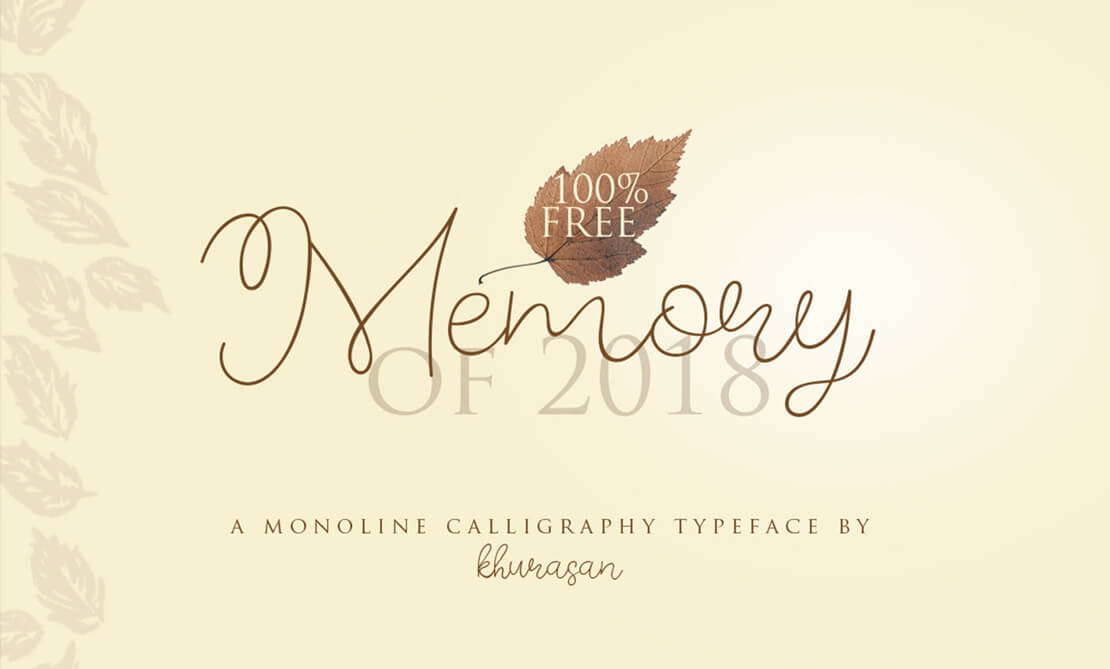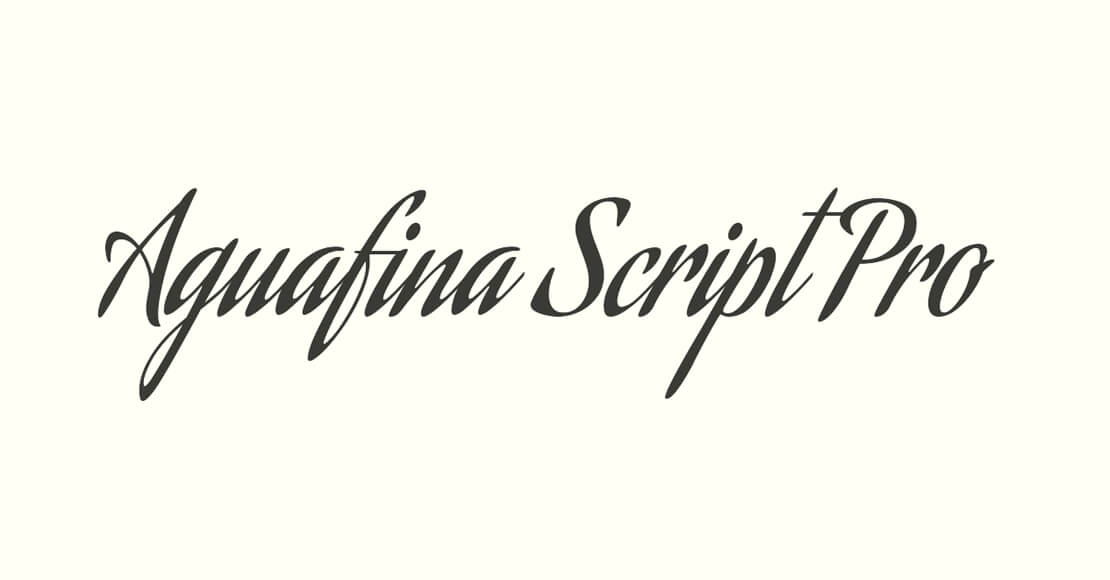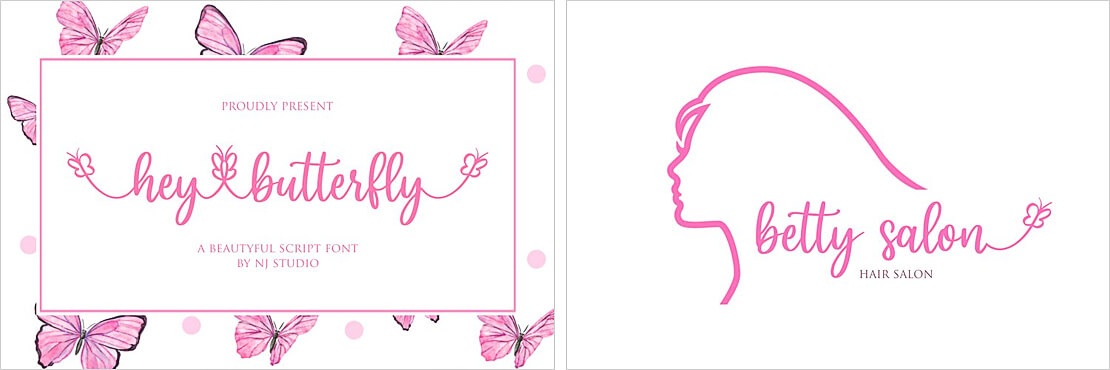
Kalligraphie-Schrift: Kostenlose Fonts zum Downloaden
Kalligraphie-Schrift ist beliebt. Moderne Fonts verwenden OpenType-Features, um die „Kunst des schönen Schreibens“ möglichst natürlich bzw. realistisch wirken zu lassen. Hier kommen ausgesuchte und zudem kostenlose Kalligraphie-Schriften.
Traditionelle und moderne Kalligraphie
Bei der Kalligraphie geht es im Grunde genommen um das schöne (kunstvolle) Schreiben. Die traditionelle Technik folgt dabei bestimmten Regeln. Diese geben beispielsweise vor, auf welche Weise Buchstaben zu formen oder auszurichten sind. Die entsprechende Ästhetik wird zumeist durch ein hohes Maß an Perfektion erreicht.In der modernen Kalligraphie hingegen spielen die klassischen Vorgaben eine eher untergeordnete Rolle. Vielmehr ist Individualität gefragt. Da darf es dann auch mal wilder zugehen. Die Persönlichkeit bzw. das Transportieren von Gefühlen, Emotionen etc. steht im Vordergrund. Somit eignen sich moderne kalligraphische Schriftarten beispielsweise auch fürs Branding von Marken, zur Verwendung in Kalendern, in persönlichen Instagram-Stories und mehr.
Alternative Zeichen, Ligaturen etc. bei Kalligraphie-Schriftarten
Moderne Kalligraphie-Schriftarten setzen verstärkt auf OpenType-Features, um eine möglichst natürlich wirkende Schriftart zu erzielen, die wie von Hand mit der Feder geschrieben aussieht.
Durch die Schrift-Technologie können verschiedene Varianten von Buchstaben in einem Font gespeichert und bei Bedarf abgerufen werden. Auch mehrere Kombinationen von Buchstaben bzw. Ligaturen sind dementsprechend möglich (beispielsweise „fl“, „st“, „ll“ etc.). Häufig findet man bei Kalligraphie-Schriftarten auch opulente Anfangsbuchstaben oder schmückende Elemente wie Striche oder weitere Ziersymbole, die ebenfalls in den Fonts fest integriert sind.
Kostenlose Kalligraphie-Schrift zum Downloaden
Endestry Kalligraphie-Schrift
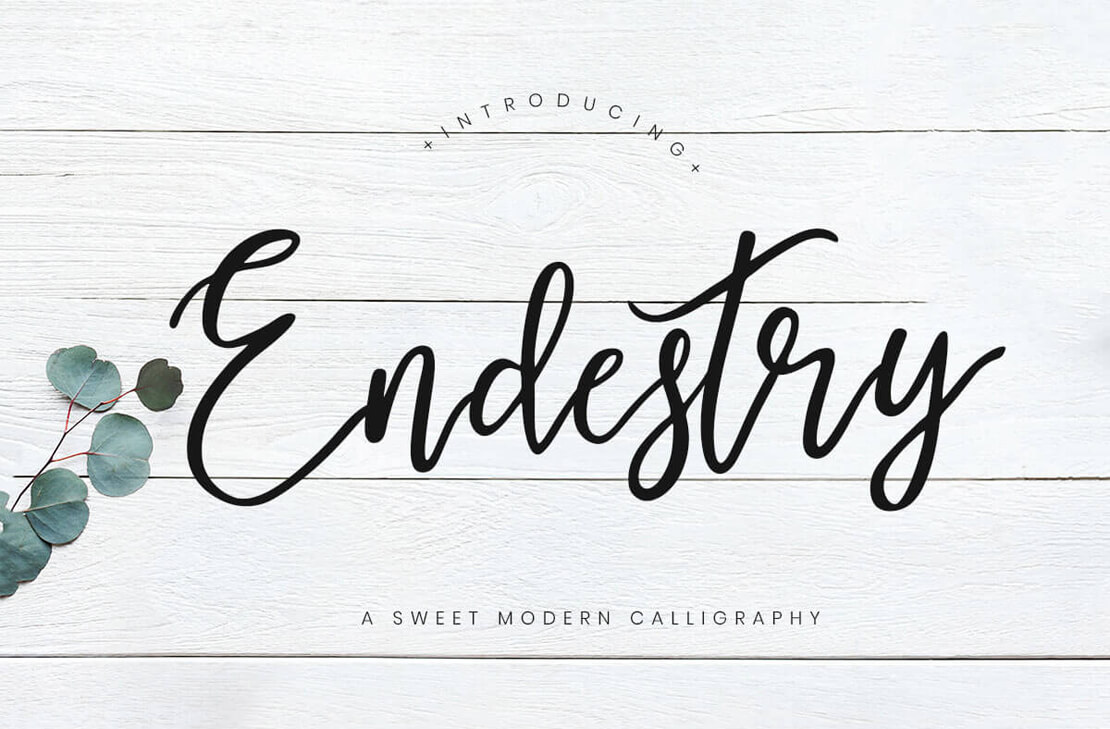
Endestry ist ein moderne Kalligraphie-Schriftart aus der Feder von Creatype Studio. Die geschmeidige Schrift sorgt zudem für eine persönliche Note und lässt sich für unterschiedliche Design-Projekte verwenden. Gemäß den Angaben auf der Website ist die Nutzung für private und kommerzielle Projekte kostenlos.
Kallem
Diese kostenlose Kalligraphie-Schriftart wurde von Khaiuns gestaltet. Der Font enthält neben Groß- und Kleinbuchstaben außerdem Symbole, Ligaturen und weitere Zeichen. Zudem werden mehrere Sprachen unterstützt. Die sogenannte „Free Version“ darf für private und kommerzielle Projekte verwendet werden. Außerdem gibt es noch eine erweiterte Version der Schrift, die noch mehr Zeichen enthält.
Basyirah Script: Kalligraphie-Schriftart
Ein Font mit ansprechender Handkalligraphie. „Basyirah Script“ lässt sich vielfältig verwenden – beispielsweise für Hochzeitseinladungen, Etiketten, Poster, Zitate, Beschilderungen und mehr. Der Download wird unter der sogenannten „Premium License“ angeboten. Dementsprechend lässt sich dieser Kalligraphie-Font für kommerzielle und private Zwecke gleichermaßen verwenden.
Rachella Script Font
„Rachella Script“ stammt Ian Mikraz Studios Sammlung von kostenlosen Kalligraphie-Schriftarten. Der Font enthält 270 Glyphen und 87 alternative Zeichen. Enthalten sind außerdem stylistische Alternativen, Ligaturen und mehr. Außerdem werden OpenType-Funktionen unterstützt. Den Free Font kann man übrigens direkt von der Website des Type-Designers herunterladen.
Mr De Haviland aus der Charles Bluemlein Script Collection
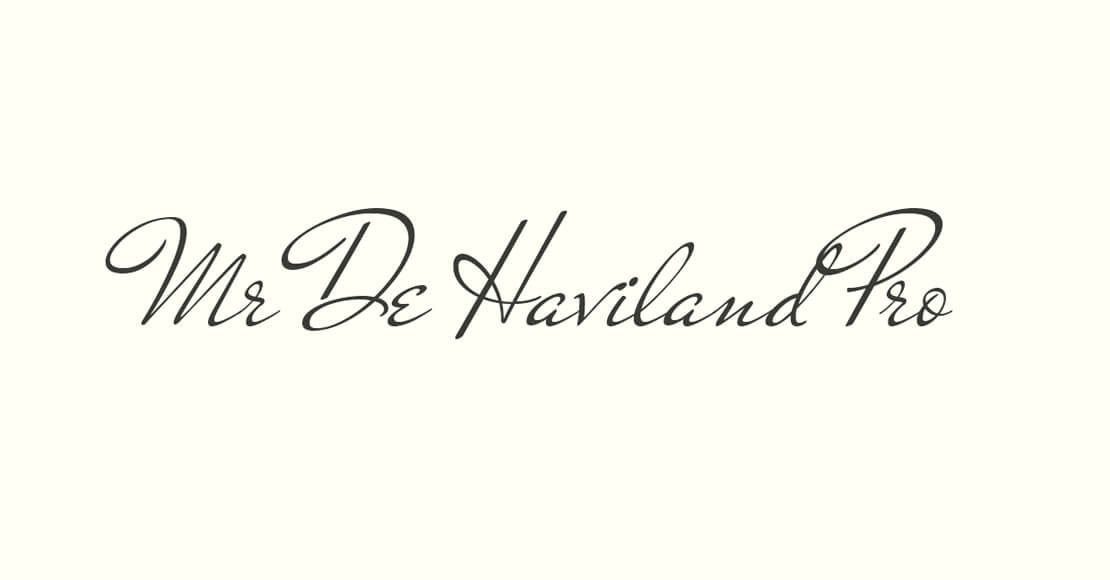
Die „Charles Bluemlein Script Collection“ ist eine Hommage an die Handschrift-Schriftarten und Kalligraphie-Fonts der frühen 1930er Jahre. Sudtipos digitalisierte sorgfältig die New Yorker Sammlung und präsentiert mit „Mr De Haviland“ eine ausdrucksstarke Schreibschrift im Kalligraphie-Stil.
Den Font gibt es übrigens bei Google Fonts kostenlos zum Downloaden. Außerdem bieten die Kreativen auf ihrer Seite eine erweiterte Pro-Version mit zusätzlichen Zeichen und Features an.
Moderne Kalligraphie-Schrift Shelly
„Shelly“ ist eine elegante Kalligraphie-Schrift mit zeitgemäßem Look. Sie wurde sichtlich inspiriert von klassischer Kalligraphie. Neben diesem Font hat der Entwickler madjack.font außerdem noch eine Reihe weiterer Kalligraphie-Schriftarten in seinem Portfolio am Start.
Sellena Kalligraphie-Schrift Duo
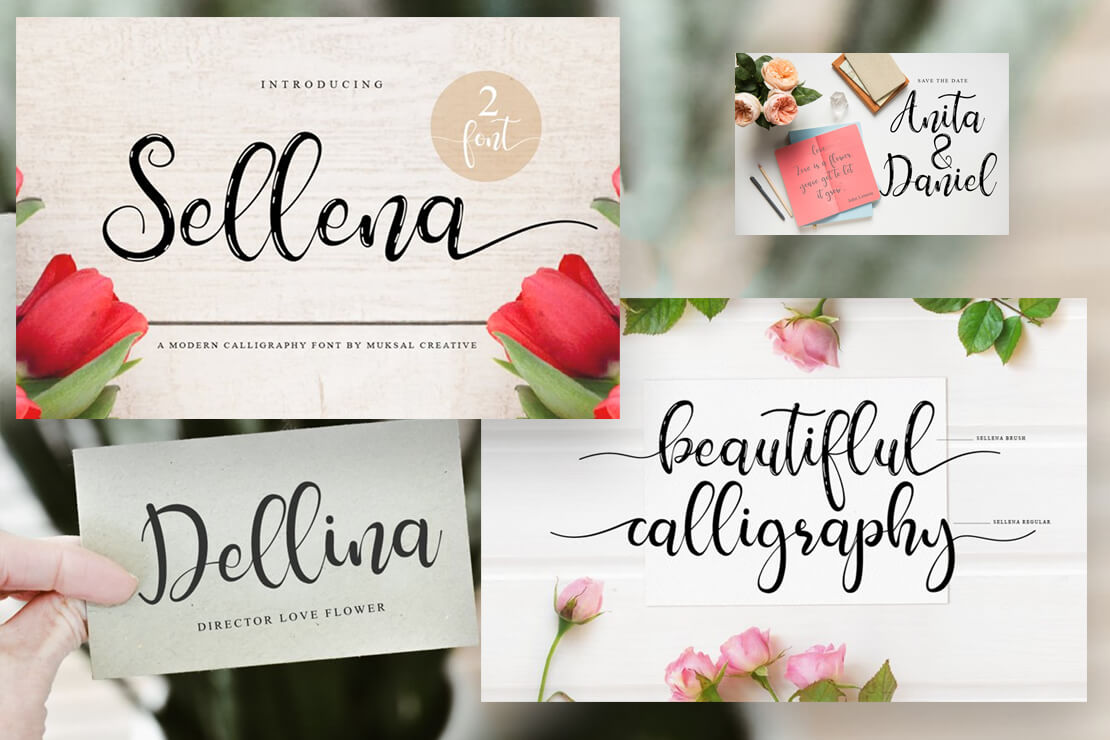
„Sellena Brush“ and „Sellena Regular“ sind Kalligraphie-Schriften im modernen Stil. Die Schreibschriften eignen sich unter anderem für Hochzeitseinladungen, Dankeskarten, Logos, Grußkarten, Zitate, Visitenkarten und Projekte, bei denen eine handschriftliche Note gefragt ist. Beide Fonts gibt es zusammen im Paket zum Downloaden. Die kostenlosen Kalligraphie-Schriftarten kommen außerdem mit einer „Premium Licence“. Sie lassen sich dementsprechend in privaten und kommerziellen Projekten verwenden.
Eleganter Kalligraphie-Font: Warton
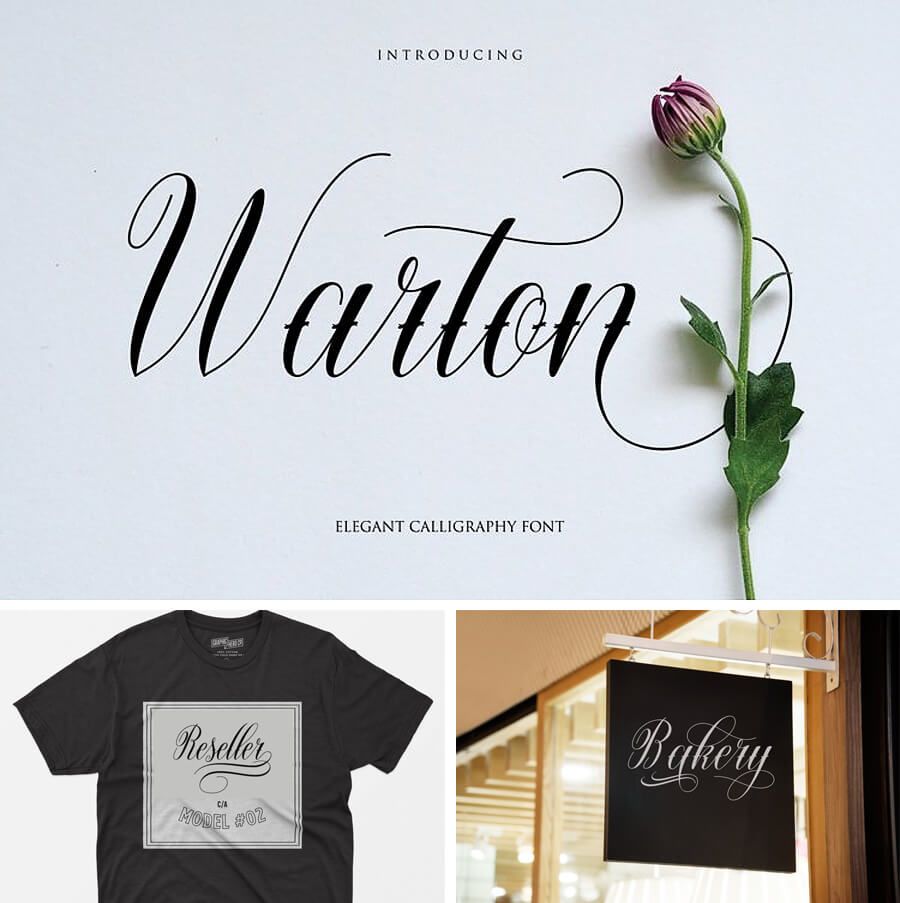
Wirkt elegant und sorgt auch mit nur wenigen Worten für eine entsprechende Wirkung: „Warton“ von Serdaribut Studio. Weitere handgemachte Fonts findet man übrigens auf der Portfolioseite des Studios.
Floristy: Florale Kalligraphie-Schrift
Florale Elemente enthält „Floristy“. Aber auch ganz ohne Blüten und Zweige macht diese Kalligraphie-Schriftart eine ansprechende Figur. Der Download wird unter der sogenannten „Premium License“ bereitgestellt. Dementsprechend ist eine Nutzung im privaten und kommerziellen Umfeld möglich.